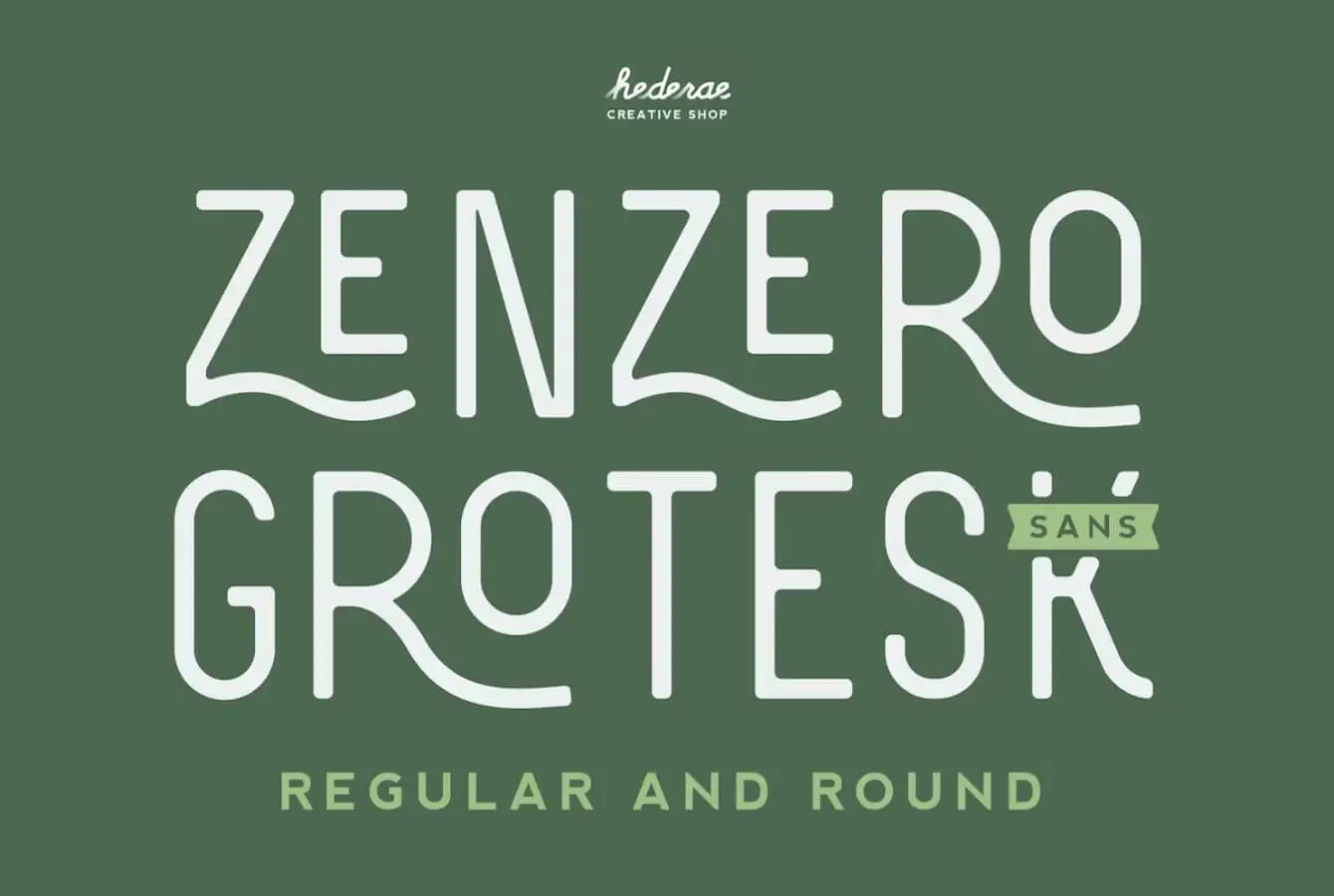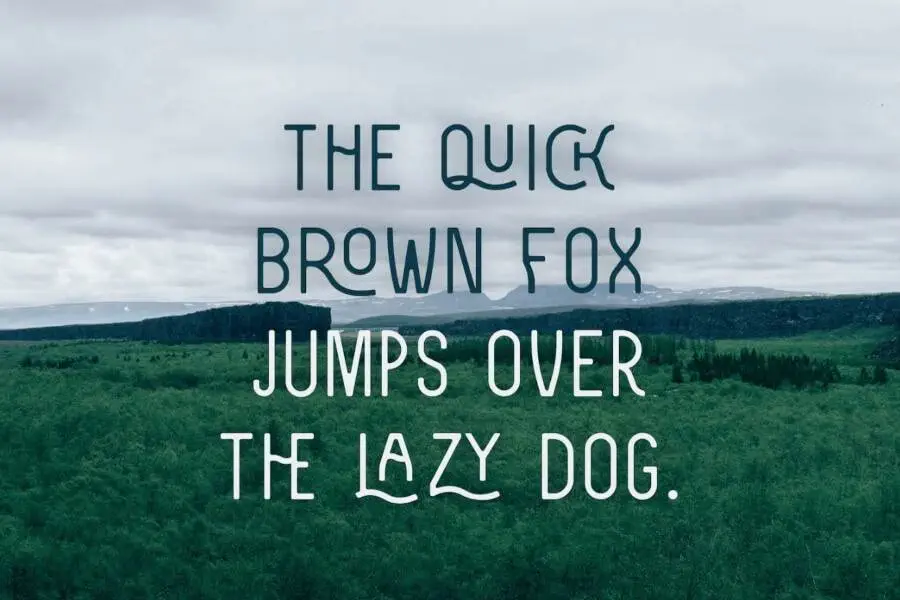
Zenzero Grotesk Sans là một font chữ dựa trên công nghiệp có thể được cung cấp cho các mục đích sử dụng khác nhau. Ưu điểm chính của nó là vô số khả năng để bạn viết từ, văn bản hoặc đoạn văn. Nó tự hào có rất nhiều chữ ghép và glyph thay thế phong cách , để kiểm soát hoàn toàn kết quả cuối cùng.
Các ngôn ngữ được hỗ trợ : Tiếng Albania, Tiếng Catalan, Tiếng Croatia, Tiếng Séc, Tiếng Đan Mạch, Tiếng Hà Lan, Quốc tế ngữ, Tiếng Estonia, Tiếng Philipin, Tiếng Phần Lan (Suomi), Tiếng Tây Frisian, Tiếng Pháp, Tiếng Hungary, Tiếng Ailen, Tiếng Ý, Tiếng Latvia, Tiếng Litva, Tiếng Na Uy, Tiếng Ba Lan, Tiếng Bồ Đào Nha, Tiếng Rumani, Tiếng Serbia , Tiếng Slovenia, Tiếng Tây Ban Nha, Tiếng Thụy Điển, Tiếng Thổ Nhĩ Kỳ, Tiếng Wales, Tiếng Anh, Tiếng Đức.